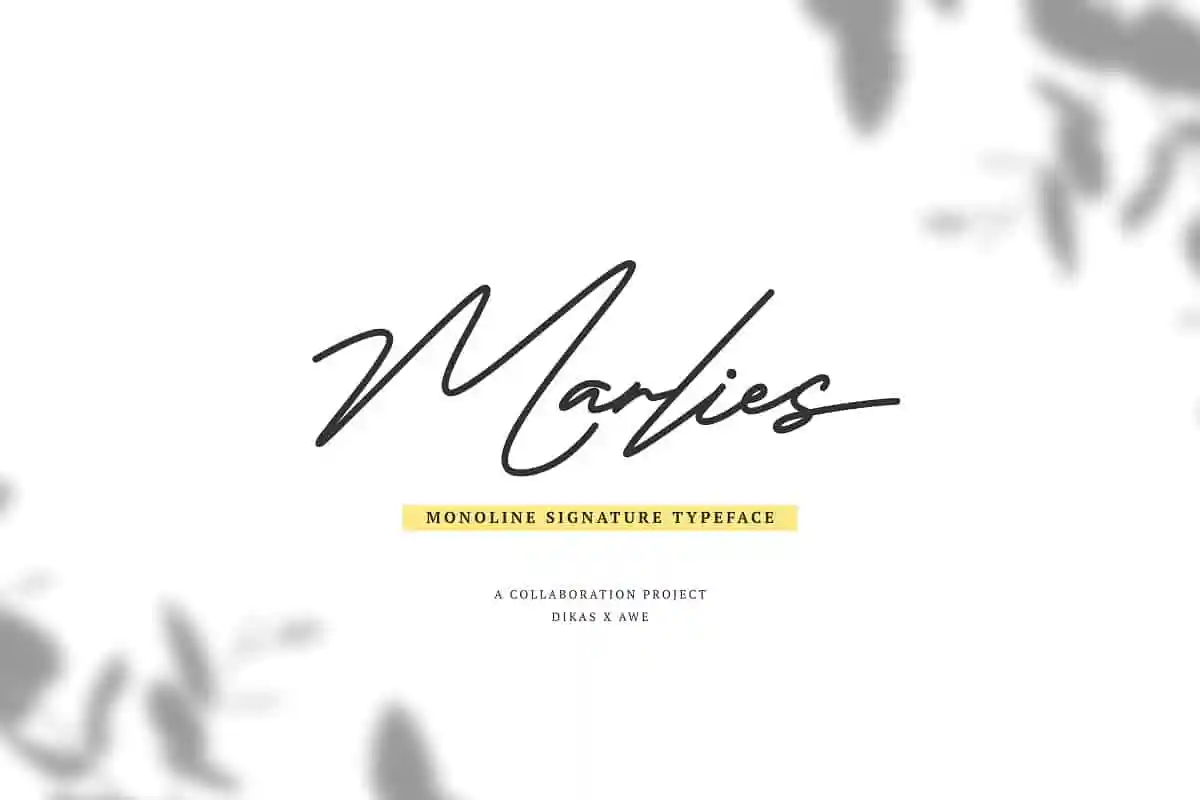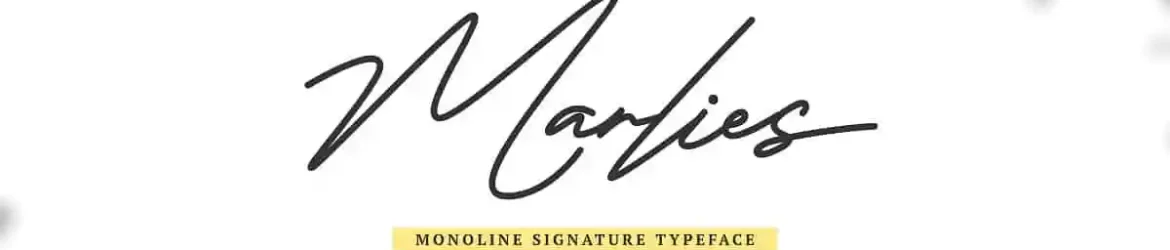
Marlies Signature Font – Download Grátis
A fonte ‘Marlies Signature Font’ é perfeita para quem busca uma mistura única entre a elegância do handwritten e as modernidades da tipografia digital. Esta font é baseada no estilo de letra escrita à mão, criando um charme especial que destaca qualquer projeto. DikasStudio produziu este tipo de letra em linha simples (‘Marlies Monoline Signature’), tornando-o ideal para uma variedade de aplicativos como criação de logomarcas, design tipográfico, cartões de natal, embalagens de produtos, convites e até mesmo camisetas. Essa font é perfeita tanto para criar um visual elegante quanto para dar um toque moderno a qualquer projeto. Suas linhas simples, com suas curvas suaves e estilo de letra escrita à mão, garantem que sua marca fique marcada e destaque-se em qualquer mídia ou plataforma onde seja usada.